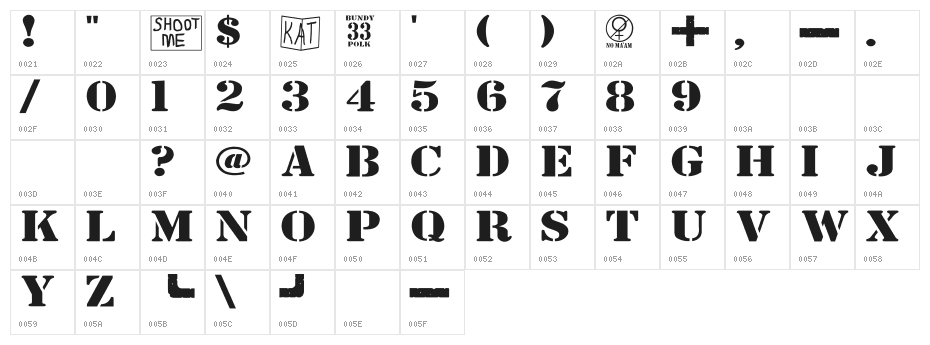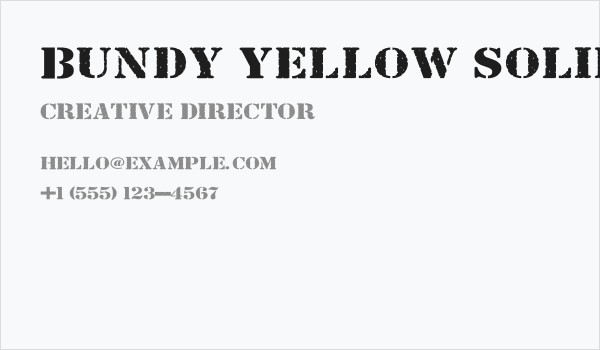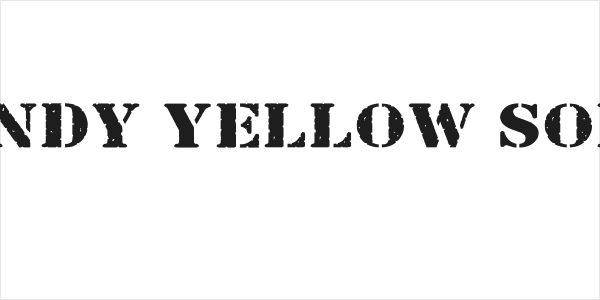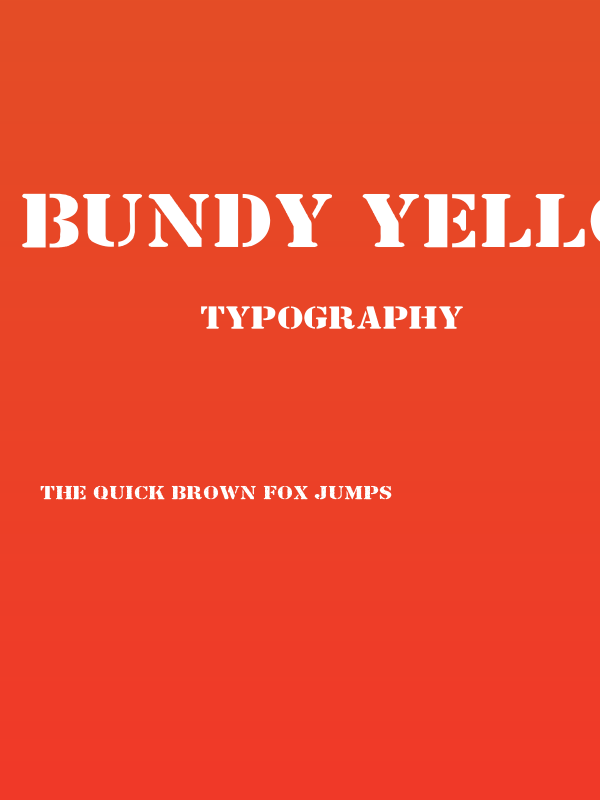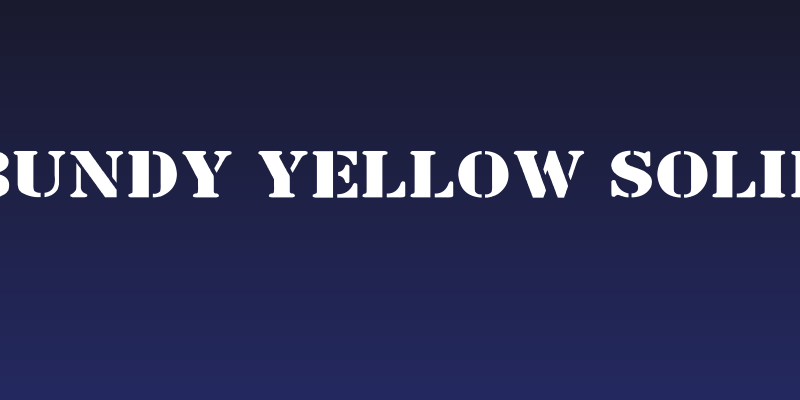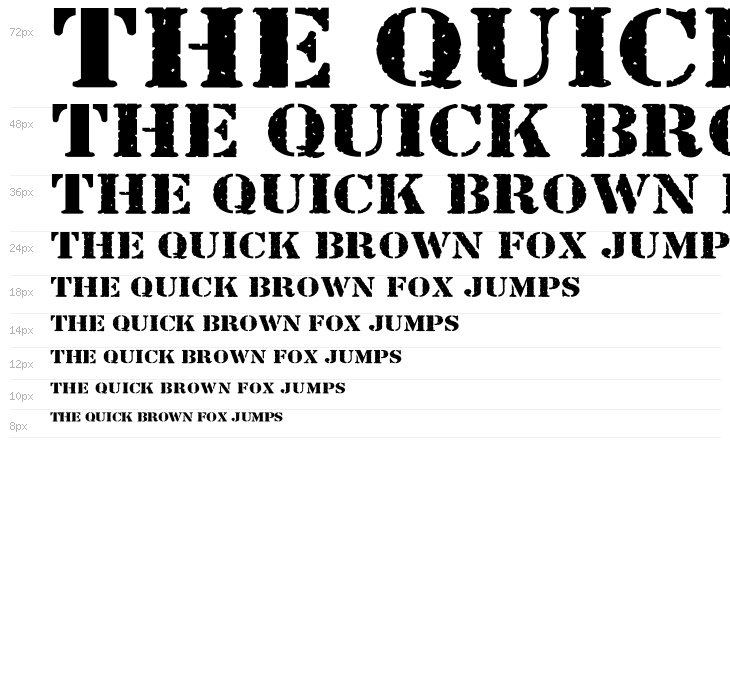
Bundy Yellow Solid Font
| 名前 | Bundy Yellow Solid |
| ウェイト | Solid |
| カテゴリ | Stencil |
| 全体的なスタイル | Vintage, Industrial |
| おすすめプロジェクト | Ideal for posters, logos, branding, and any design requiring a strong, vintage industrial aesthetic. |